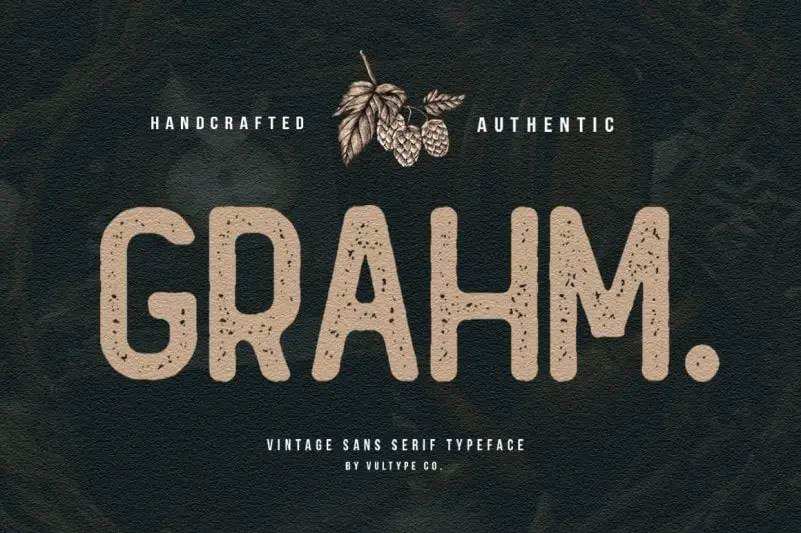
Grahm Display Font – Fonte Grátis
Grahm Display Font
A fonte Grahm Display é uma escolha perfeita para projetos que buscam elementos naturais e vintage ao mesmo tempo. Seu design com conceitos do mundo exterior leva a um resultado autêntico, ideal tanto como a fonte principal quanto como recurso complementar em trabalhos de desenvolvimento de marca. Esse tipo de fonte é uma criação da Vultype para o gosto das pessoas que valorizam os elementos da natureza e tem a aparência casual dos serifos sans-serif, incluindo as opções Régular e Rough. Ela foi cuidadosamente projetada para se adequar a qualquer projeto, sendo especialmente ótima para logotipos, design de marca, letras digitais, arte em camisetas e roupas, cartazes, publicações, anúncios e qualquer necessidade vintage. A Grahm Display é uma font perfeita que combina o desafio do cotidiano com a leveza da natureza num só projeto.